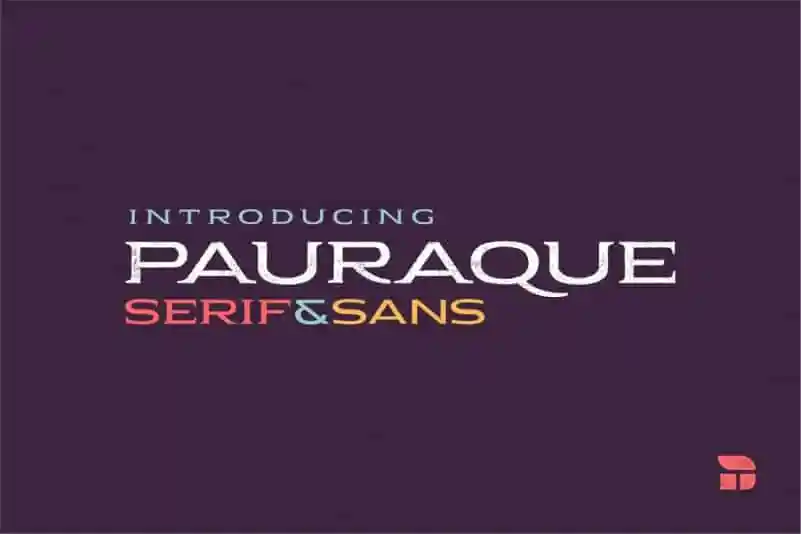
A Pauraque Display Font é uma opção irresistível para designers buscando algo único no seu próximo projeto. Essa fonte orgânica com vibrações naturais foi criada pelo experiente designer NimaVisual, disponível neste marketplace de 99designs. É um texto moderno e elegante que se destaca por sua simplicidade visual, mantendo-se ao mesmo tempo minimalista e geometricamente construído. Com uma aparência inovadora e revolucionária, a Pauraque Display é perfeita para incorporar em vários tipos de projetos gráficos – seja na criação de logotipos, rótulos ou qualquer outro trabalho visual. A escolha da Pauraque pode transformar seu design em algo único, com uma combinação única de elegância e modernidade que certamente chamará a atenção dos usuários finais.